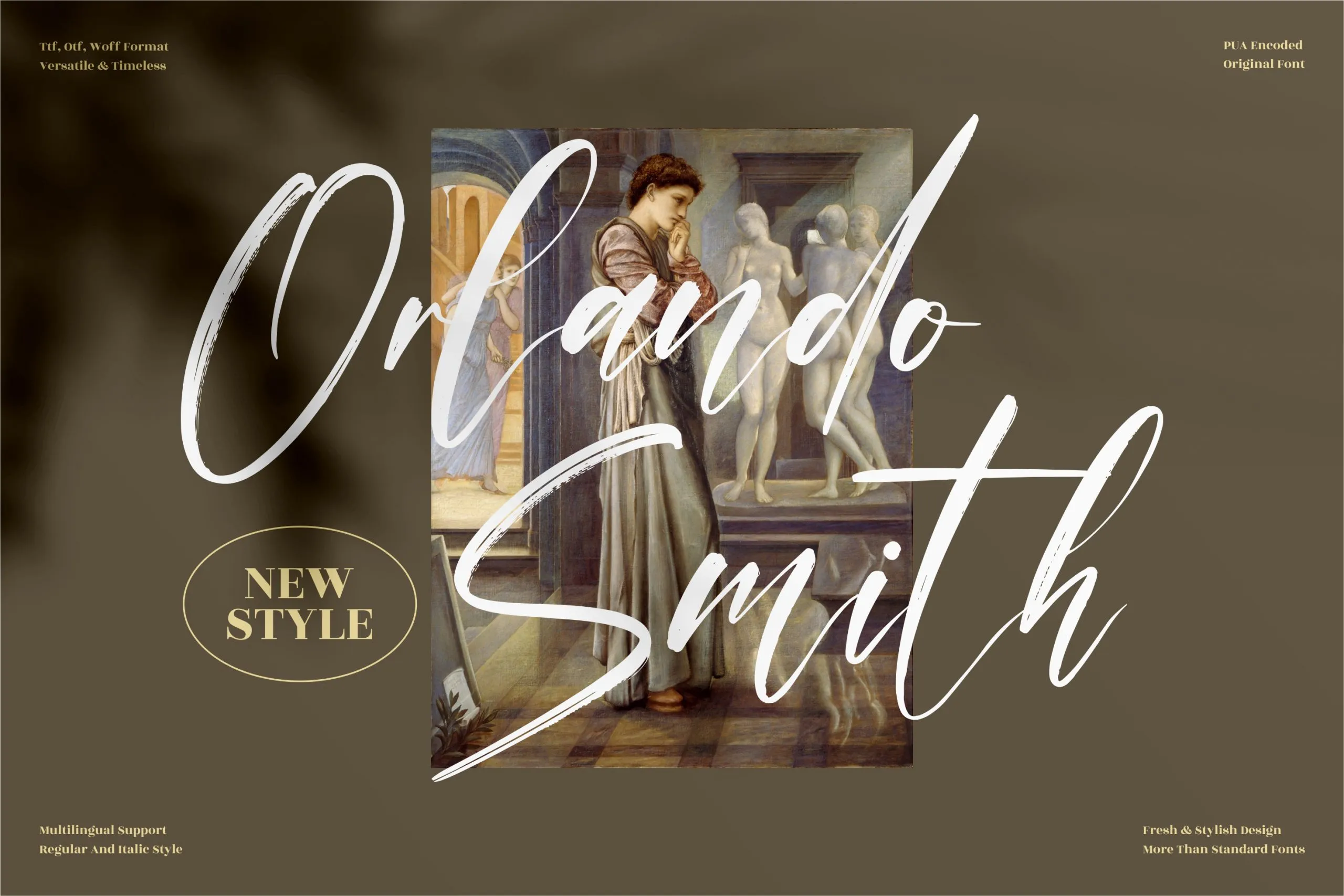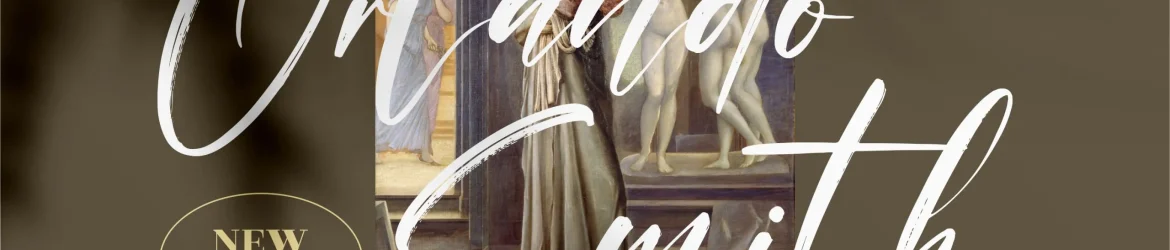
Orlando Smith Font – Download Grátis
A Fonte Orlando Smith é perfeitamente adequada para projetos que valorizam uma mão-direita única e autêntica. Seja você criando identidades de marca, design de móveis, embalagens de produtos, t-shirts ou capas de livros, a Orlando Smith oferece um toque único que complementa qualquer projeto. Perfeita para projetos luxuosos como cartões de nome, convites e cartões de agradecimento, essa fonte também atende bem à fotografia, marcas d’água para camadas de conteúdo ou eventos especiais. Além disso, ela é perfeita para criações em papelaria, como sacolas de shopping, porta-revistas e adesivos personalizados, transmitindo uma sensação de sofisticação e individualismo. Com o designer perspectype, a Orland Smith Font tem a capacidade de dar um toque único aos seus trabalhos. Ela é perfeitamente adaptada para projetos que precisam de um ar autêntico e handwritten. Esta fonte foi especialmente criada para aqueles que buscam personalizar sua identidade visual de forma única, trazendo uma sensação única a qualquer projeto. Essencialmente uma fonte brush (ou letra cursiva), ela é perfeita tanto para uso em grandes projetos como pequenos detalhes. Ela oferece um toque único e autêntico que se assemelha ao grafismo manuscrito, tornando-a uma excelente escolha para seus projetos de design gráfico.